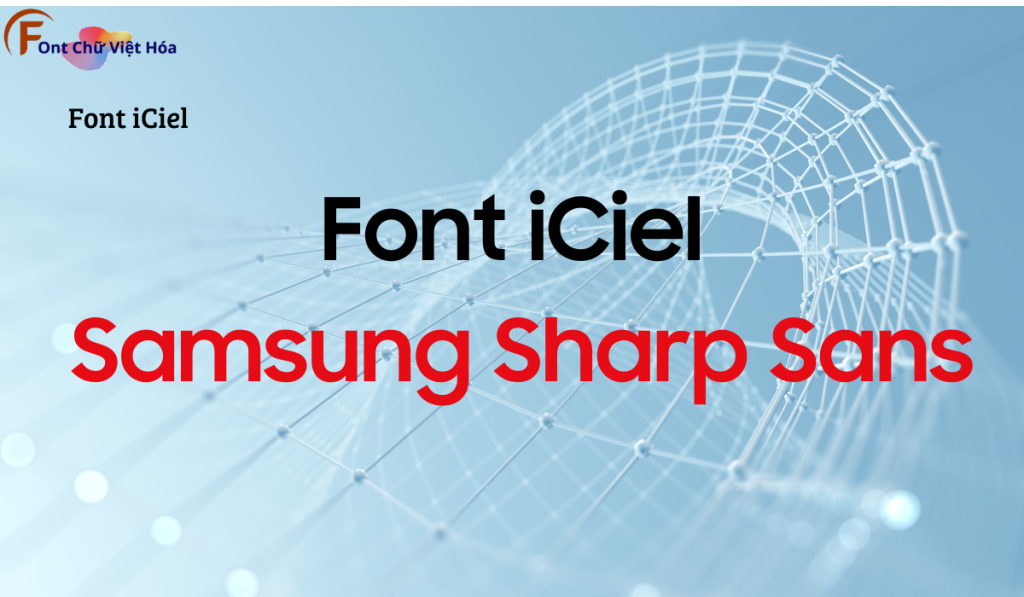
Font iCiel Samsung Sharp Sans Việt Hóa
Phân loại: Cá tính, Hiện đại
Kiểu chữ: Sans-serif
Độ dày: Regular, Medium, Bold
Font iCiel Samsung Sharp Sans Việt Hóa, thuộc bộ font iCiel, là font sans-serif hiện đại, nổi bật với các nét chữ rõ ràng và độ dày đa dạng. Font này có các đường nét gọn gàng, dễ đọc, tạo cảm giác sáng tạo và chuyên nghiệp. Font iCiel Samsung Sharp Sans Việt Hóa lý tưởng cho các dự án thiết kế như thiệp mời, bìa sách, và tài liệu văn phòng. Việc Việt hóa font giúp người dùng dễ dàng tích hợp vào các thiết kế tiếng Việt, mang lại sự tiện lợi và nâng cao tính thẩm mỹ.